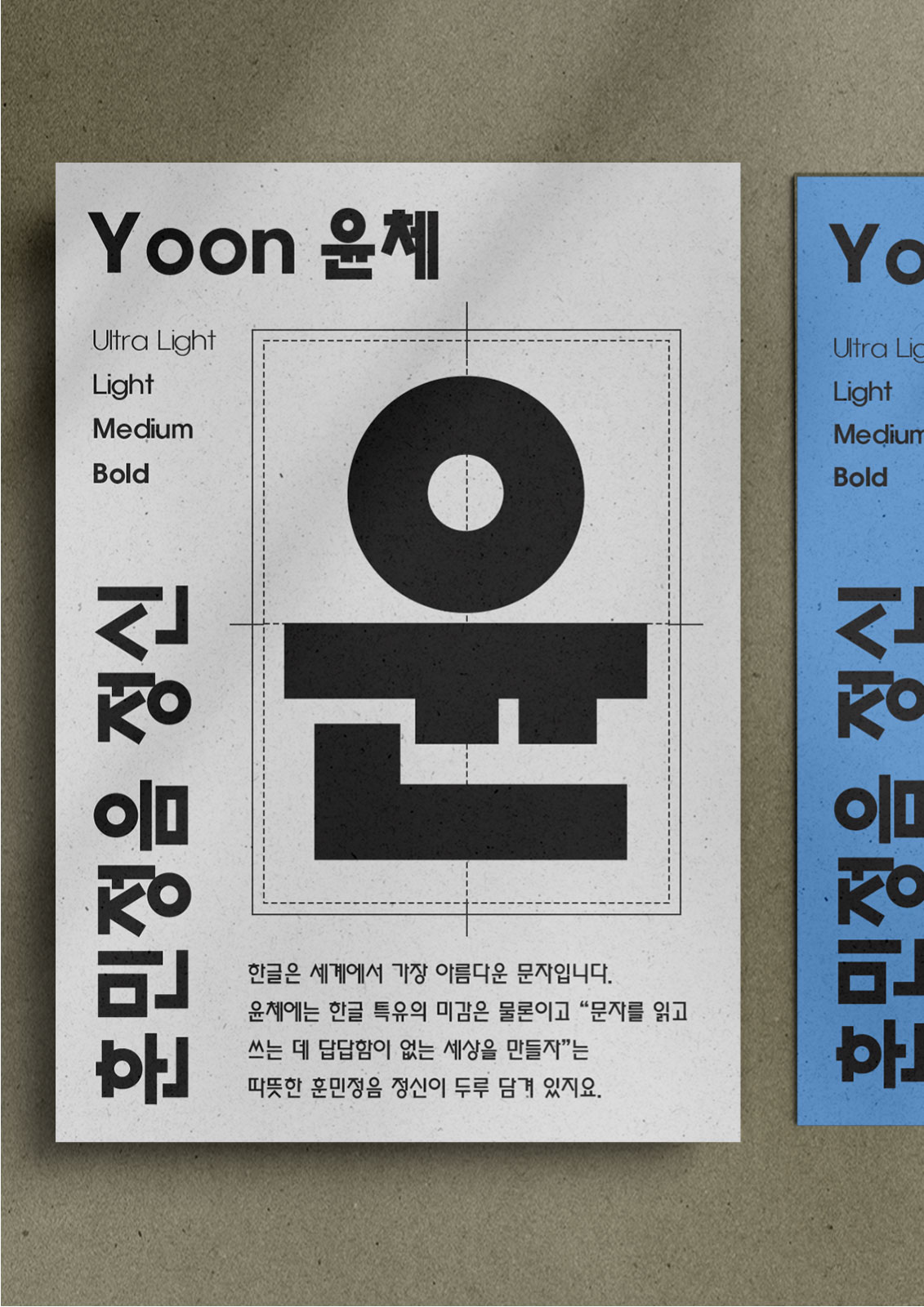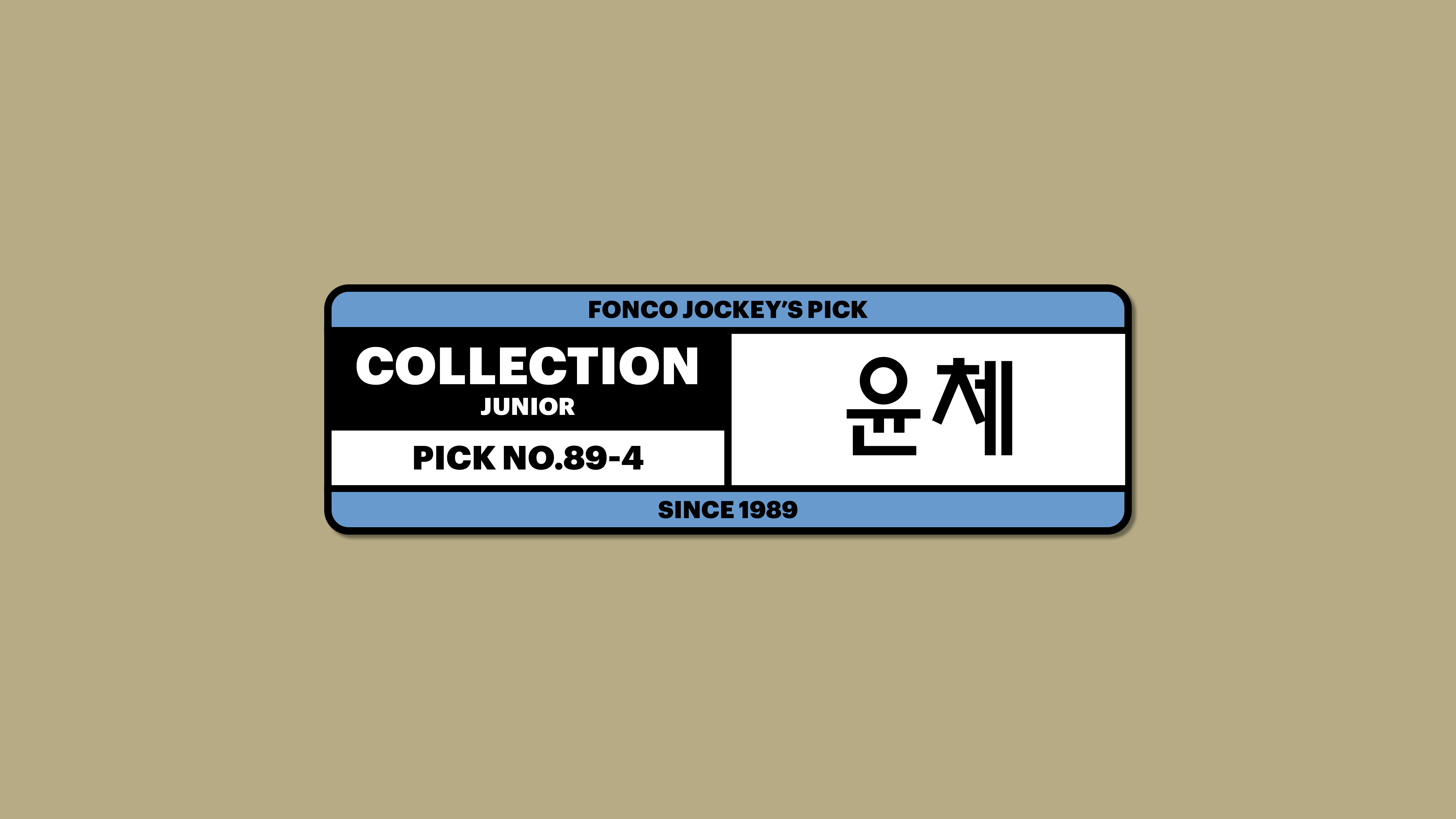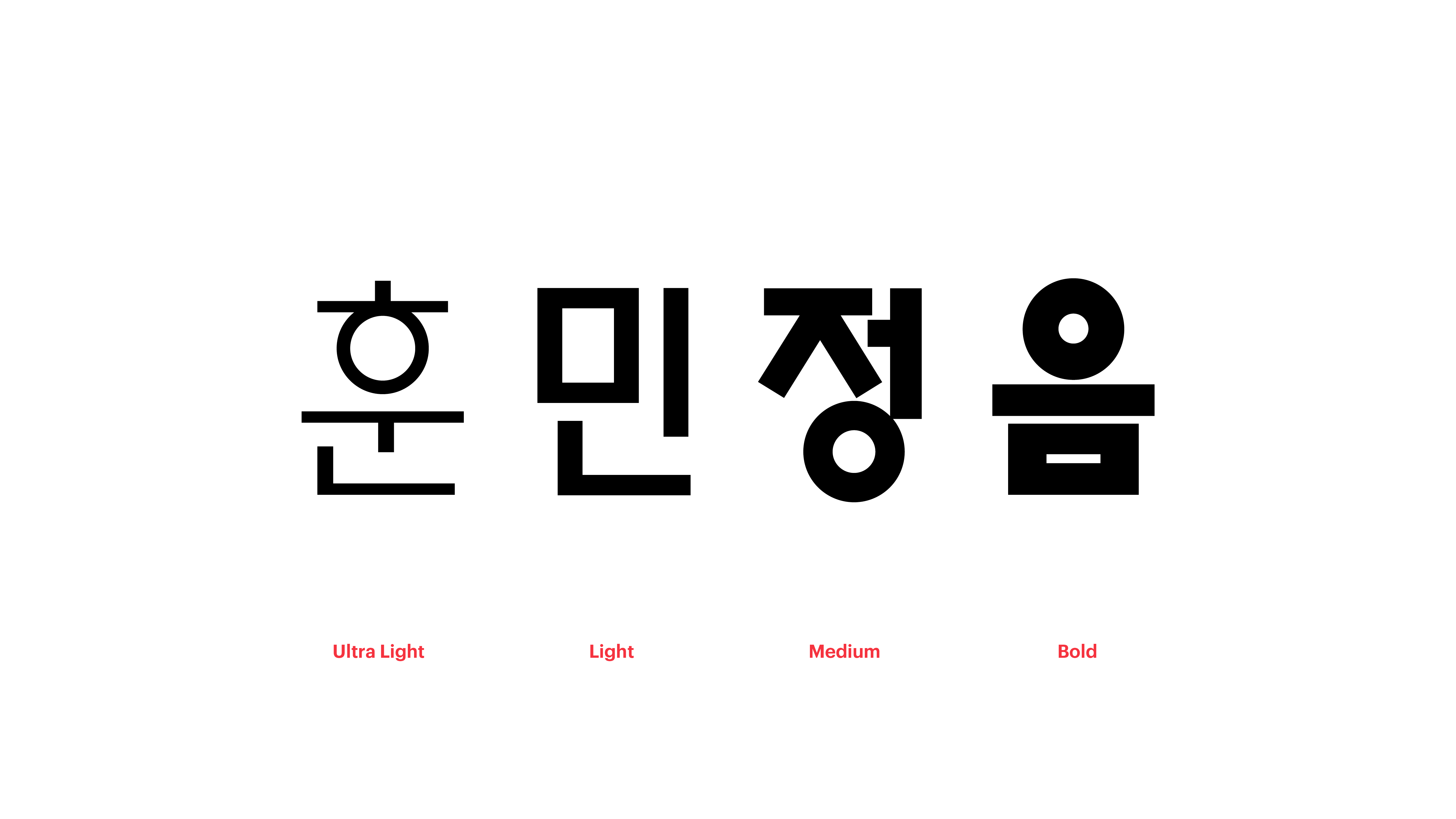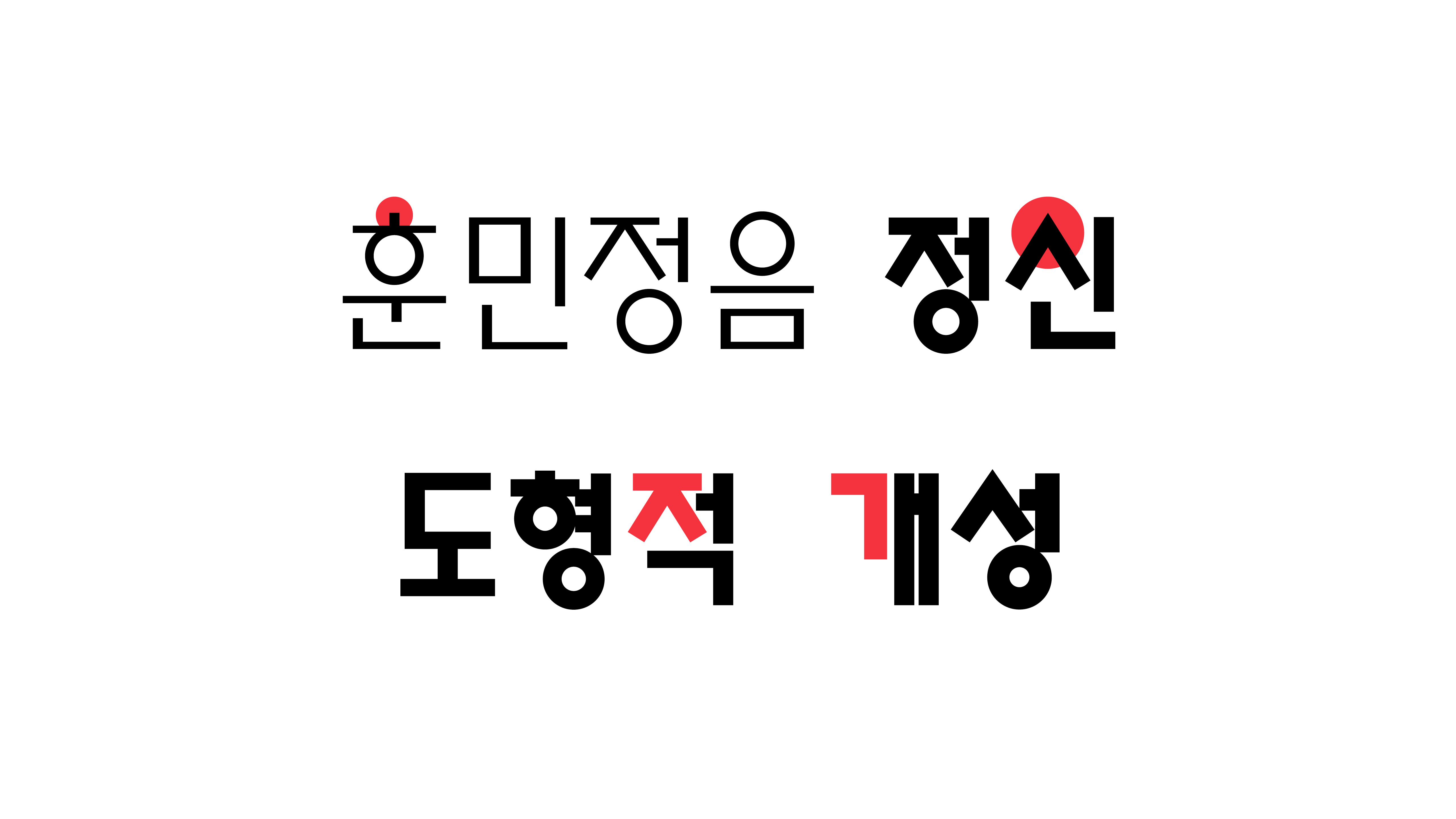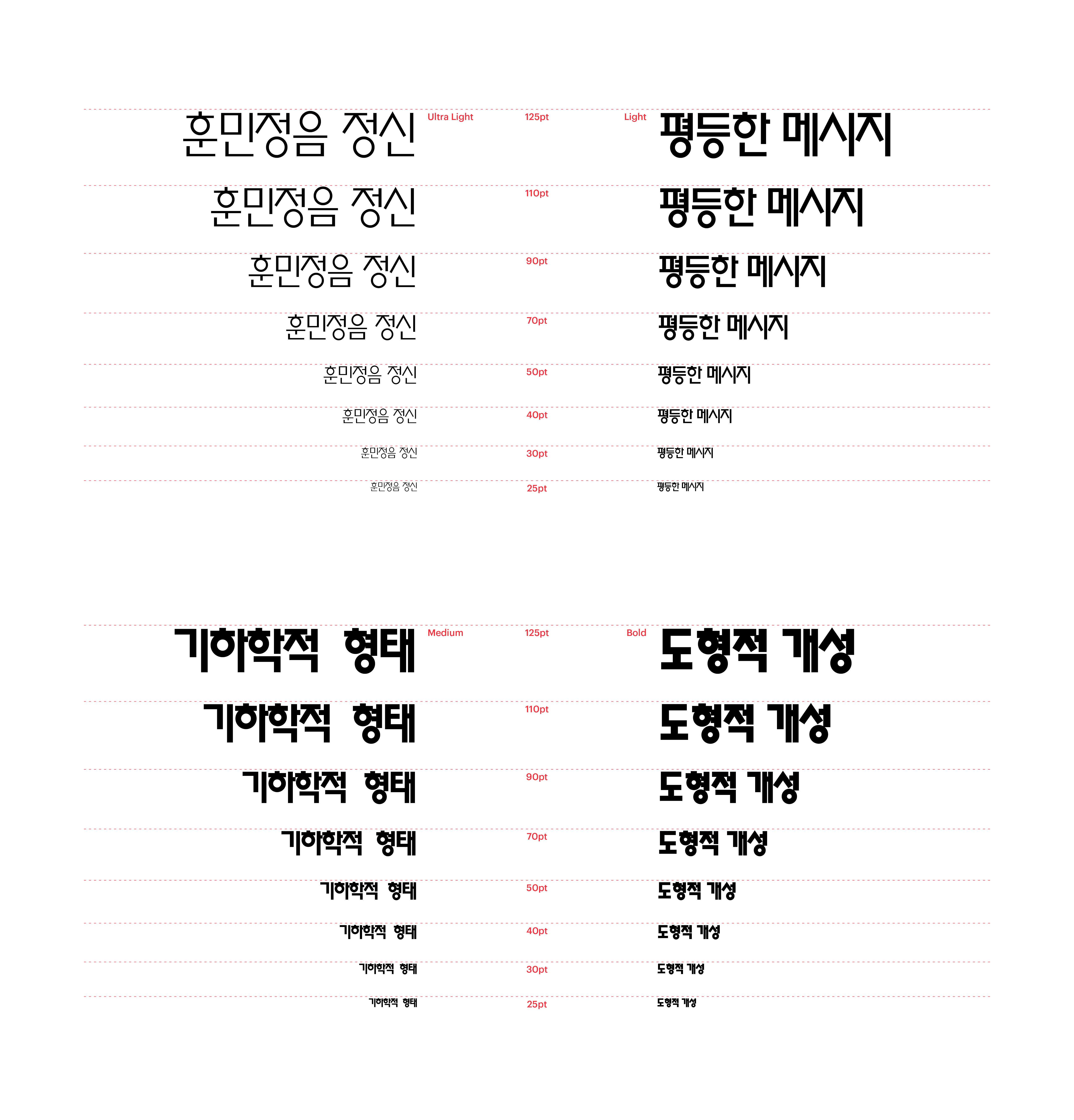
1985-1989
한글은 세계에서 가장 아름다운 문자입니다. 윤체에는 한글 특유의 미감은 물론이고 “문자를 읽고 쓰는 데 답답함이 없는 세상을 만들자”는 따뜻한 훈민정음 정신이 두루 담겨 있지요. ㅁ, ㅇ, ㅎ의 기하학적 형태가 강조된 개성적 생김, 문자 본연의 철학을 환기하는 평등한 메시지. 가장 한글다운 폰트인 윤체가 우리의 한글 생활을 응원합니다.
Yoon 윤체